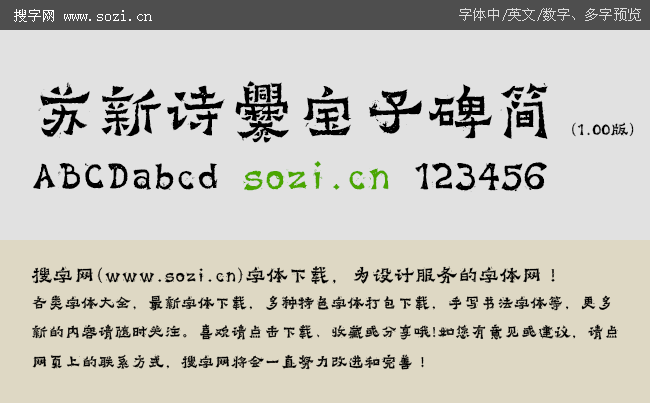
蘇新詩爨寶子碑簡(jiǎn)
搜字網(wǎng)提供一款蘇新詩爨寶子碑簡(jiǎn)中文字體下載,, 蘇新詩爨寶子碑簡(jiǎn)是一款應(yīng)用于書法方面的簡(jiǎn)體中文漢字,該字體以碑體為原形,筆鋒犀利,字形大小適中,并且字庫完整,整體效果十分出眾,適合應(yīng)用于廣告設(shè)計(jì)、名片設(shè)計(jì)、包裝印刷、產(chǎn)品設(shè)計(jì)等應(yīng)用。